漢字の構成と制作ポイント04「囲む系」
囲む系の部首には「垂(たれ)」「繞(にょう)」「構(かまえ)」があります。囲む側は強め、中に入るものは弱めに見えるよう大きさを調整します。太さについては中に入るものを一段階細く作り、混雑を避け文字全体のトーンをならします。特に太いウエイトになるほどこの一段階で大きく差をつける傾向があります。以前紹介した「縦画は右に行くほど太く、横画は下に行くほど太く」という原則がありますが、これは囲む側と入る側で別々に考えて調整しています。
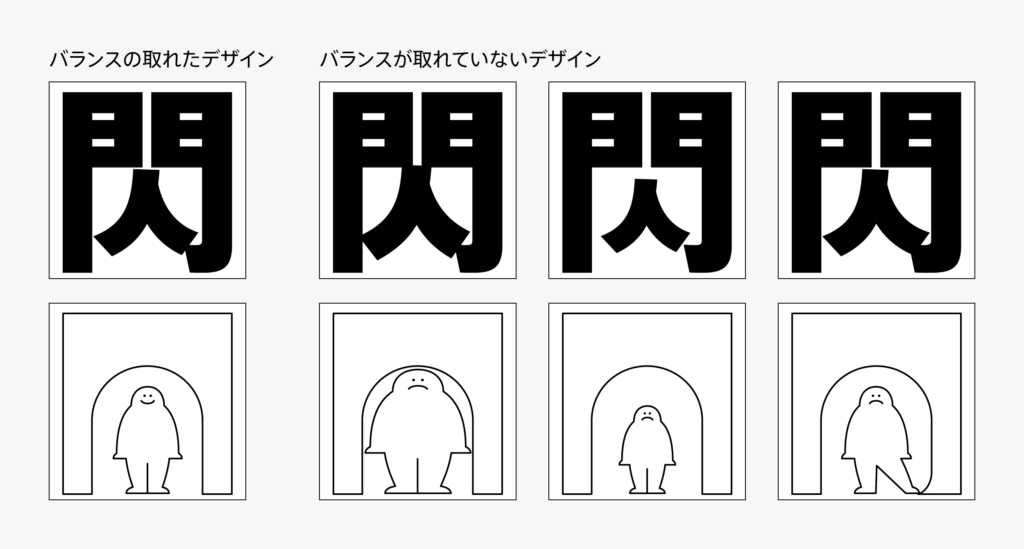
あとは他のグルーブと同じく各要素の形状に合わせた調整です。たとえば「閃」で「門」のハネと「人」の右ハライがぶつかりそうなら、どちらか又は両方を短くするといった調整を入れたりしています。